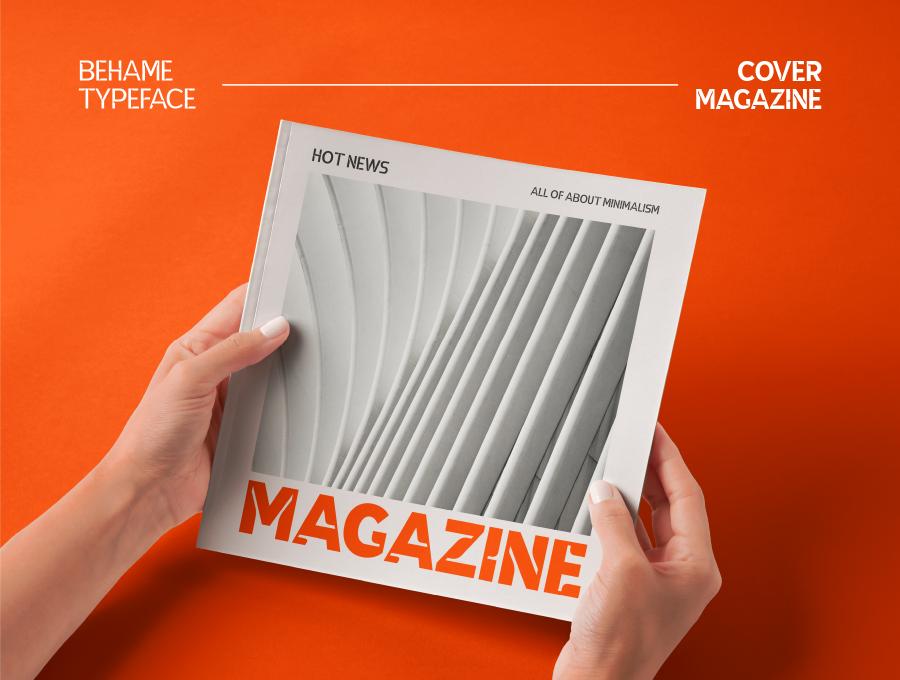
Behame - Futuristic Sans Serif 现代无衬线字体与锐利的墨迹,提供一个动态和未来的外观
Behame是一种光滑的无衬线字体,每个字形都有干净、精确的墨迹,给人一种独特的未来感和现代感。动态设计提供了一种运动感和清晰度,使其完美的尖端品牌和技术为重点的设计。从浅色到黑色的各种风格可供选择,每种重量都有斜体选择,Behame的多功能性和时尚的墨迹细节使其成为粗体标题和精致正文的绝佳选择。其独特的功能提供了动态而干净的外观,非常适合需要前瞻性美学的项目。